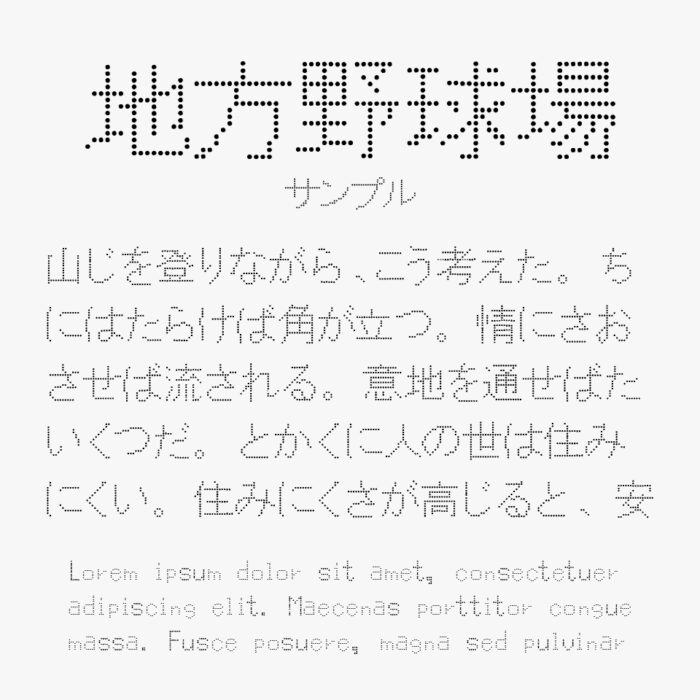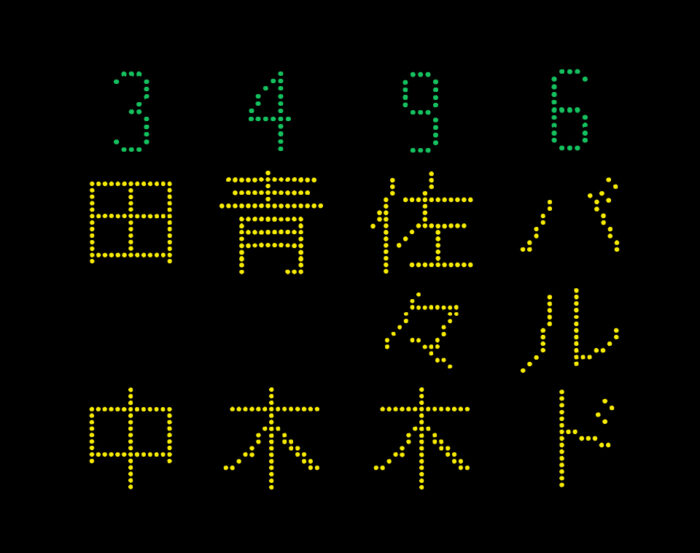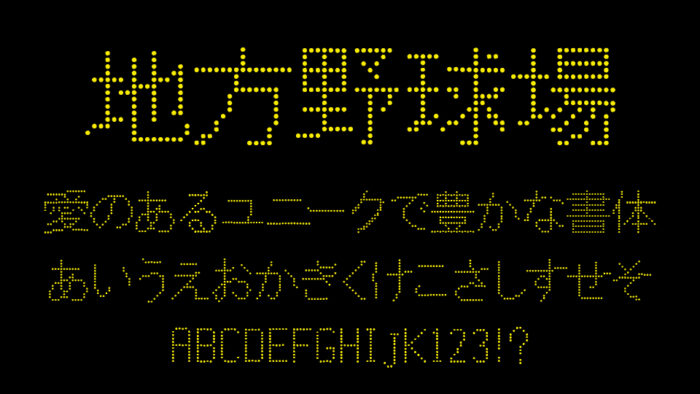
地方野球場電光掲示板フォントは、ドットで構成された文字で、80年代神宮球場や地方野球場の電光掲示板を再現ができるデザインフォントです。
昭和の野球場でよく見られた電光スコアボードの文字をモチーフとしているドット文字になっているので、野球場以外の電光掲示板風デザインに制作する際に最適なフォントです。
電光掲示板風に配色してみると、野球のスコアボードを再現できるユニークなフォントです。